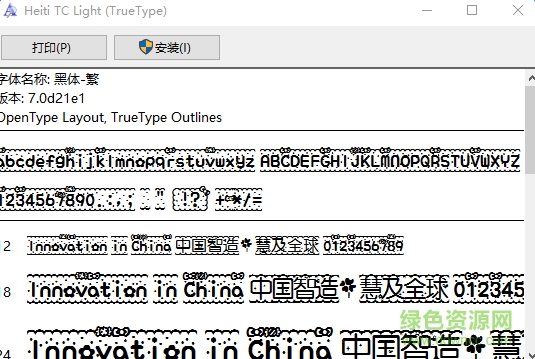
小呀嘛小餅干
小呀嘛小餅干字體是一款很有特色的電腦藝術(shù)字體,這款字體寫出來的字是很美觀的,而且實(shí)用性強(qiáng),可以用于很多方面,特別是藝術(shù)設(shè)計(jì)方面還是很不錯(cuò)的,歡迎有需要的朋友來綠色資源網(wǎng)下載。
小呀嘛小餅干字體是一款很有個(gè)性的電腦個(gè)性字體,也正是因?yàn)樗容^有個(gè)性,所以深受廣大朋友們的喜歡,歡迎大家來綠色資源網(wǎng)下載。